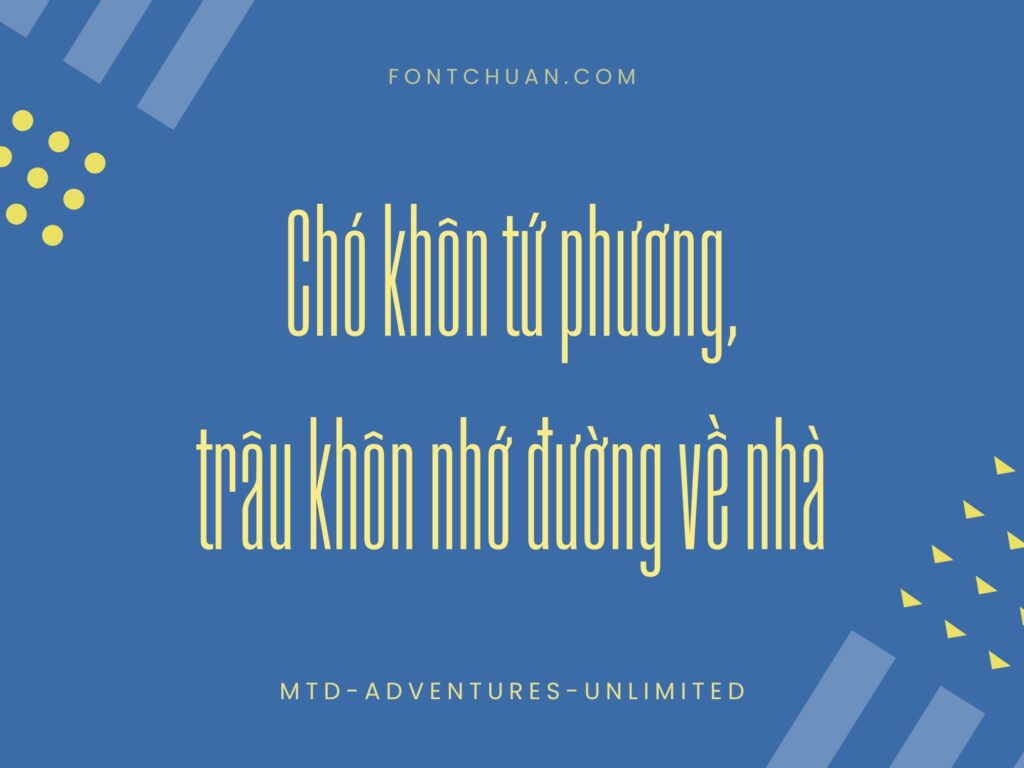
Font MTD Adventures Việt Hóa
Font MTD Adventures Unlimited Sans là một kiểu chữ sans-serif hiện đại, được thiết kế bởi Elena Genova từ My Creative Land và đã được Việt hóa bởi Mộc Hạ. Font này hỗ trợ đầy đủ tiếng Việt cùng hơn 90 ngôn ngữ khác, mở rộng khả năng ứng dụng trong các thiết kế đa ngôn ngữ. Đây là một trong những phông chữ được cộng đồng thiết kế đánh giá cao và sử dụng trong nhiều dự án sáng tạo, đáp ứng nhu cầu đa dạng của người dùng.
MTD Adventures Unlimited Sans nổi bật với các đường nét gọn gàng và cân đối, mang đến cảm giác chuyên nghiệp và thân thiện. Font rất phù hợp cho các thiết kế logo, tiêu đề, bao bì sản phẩm, thiệp mời và các ấn phẩm đòi hỏi sự hiện đại và tinh tế. Các ngành nghề phù hợp bao gồm quảng cáo, giáo dục, công nghệ, thiệp cưới và ảnh cưới. Font này cũng lý tưởng cho các sự kiện như Tết, Giáng sinh, Valentine và các lễ hội khác.